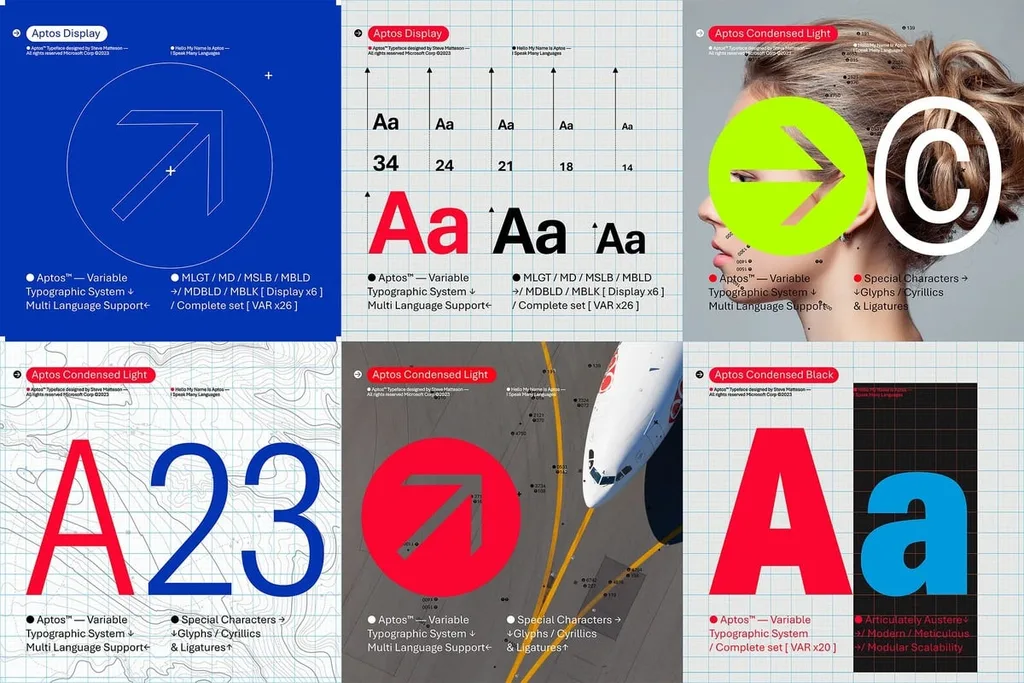
Microsoft, varsayılan fontu Calibri’yi, orta 20. yüzyıl İsviçre tipografisinden esinlenen yeni bir sans-serif tipi olan Aptos ile değiştiriyor. Daha önce Bierstadt olarak bilinen bu font, Microsoft’un son birkaç yıldır yeni varsayılan fontunu arama sürecinin bir parçasıydı. Yazılım devi, 2021’de Microsoft Office için beş yeni özel font sipariş etti ve Aptos fontu, yıllar süren geri bildirimler sonucunda varsayılan olarak seçildi.
Microsoft’un baş tasarım yöneticisi Si Daniels, perşembe günü yayınlanan bir blog yazısında, “Bugün, Aptos’un Word, Outlook, PowerPoint ve Excel’de yüz milyonlarca kullanıcı için yeni varsayılan font olarak belirmeye başladığı bu büyük değişikliğin son aşamasına başlıyoruz.” dedi. “Ve önümüzdeki birkaç ay içinde tüm müşterilerimiz için varsayılan olacak.”
Aptos, önde gelen tipograf Steve Matteson tarafından oluşturuldu. Matteson daha önce de Segoe’yi hazırlamıştı. O yazı tipi de Microsoft tarafından Windows’un varsayılan fontu olarak kullanılmak üzere lisanslanmıştı. Microsoft, Segoe UI font alt ailesini ilk olarak Windows Vista’da kullanmaya başladı ve bugün Windows 11’de hâlâ kullanılıyor. Bunlara ek olarak Matteson, orijinal Windows TrueType çekirdek fontlarının geliştirilmesi üzerinde de çalıştı. Bierstadt, Matteson’un Kaliforniya, Santa Cruz’daki favori belediye dışı kasabası olan Aptos ile yeniden adlandırıldı.
Microsoft Office’deki Aptos fontunun öne çıkan özellikleri
Aptos’un çizgi bitişleri çok net bir şekilde kesiliyor, ancak bu tip bir fontta tipik olarak bulduğunuz sert ızgara tabanlı tipografiyi önlemek için bazı ince yumuşatmalar var. Helvetica, bu tür “grotesk san-serif” fontun en ünlü örneği ve Matteson, burada Microsoft’un Arial fontu ile karşılaştırma yapıyor.
Aptos, varsayılan olarak Calibri’nin yerini alacak olsa da, eski font hâlâ yeni bir font menüsünün (ilk olarak web’de kullanılabilir) en üstünde, önceki halefleri Times New Roman ve Arial ile birlikte sabitlenmiş durumda bulunuyor.
Calibri, Office 2007’nin çıkışından bu yana varsayılan Office fontu oldu ve o zamanlar varsayılan olan Times New Roman’ın yerini aldı. Calibri o kadar yaygın kullanılıyor ki, 2017’de Pakistan’ın başbakanı etrafında dönen bir yolsuzluk soruşturmasında bile önemli bir kanıt parçası oldu. Ancak herkes yıllardır Calibri’yi kullanmıyor.
ABD Dışişleri Bakanlığı ise, bu yılın başlarında yazılı emirler için Calibri kullanmaya yönlendirmişti. Dışişleri Bakanlığı, 2004’ten beri Times New Roman kullanıyordu. Calibri’ye tamamen geçmeleri tam 16 yıl sürdü, bu yüzden muhtemelen Aptos’a geçmek için bir on yıl veya daha fazla bekleyecekler.
Varsayılan olarak seçilmeyen diğer dört font; Grandview, Seaford, Skeena ve Tenorite de Office’te mevcut olacak. Microsoft, Bierstadt fontunu da, zaten onunla tanışmış olanlar için açılır font seçicisi içinde tutacak.
Daniels, “Aptos, Microsoft 365’e gelen daha geniş bir özellik dalgasının bir parçası. Yazılımı daha ifade gücü yüksek ve kapsayıcı hale getirmek için çabalıyoruz,” diye açıklıyor. “Yeni tasarlanmış bir font seçici deneyimi, yeni temalar, renkler ve arka planlar var.”